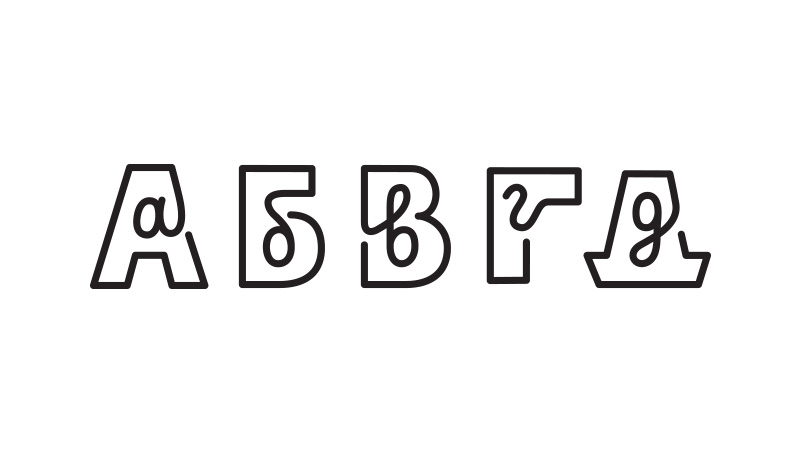
Шрифт из одной линии для обработки «по вектору» — Вопросы по шрифтам
Не в первый раз возникает необходимость написать что-нибудь эдакое одной линией.. Так, сейчас немаленький заказик на изготовление металлических штампиков для оттиска по пластилину.. Кто как выходит из положения? (я как-то давнееенько баловался- свой шрифт делал.. Убей- не помню- в какой программе, как и зачем
На сколько я понимаю, но нельзя создать линейный шрифт ни TTF-ный ни посткриптовый — т.
к. они по своей природе должны быть залитыми контурами…. Может я не прав — тогда опровергните — буду только рад…
Для номерков я нарисовал (вернее племяшку попросил — ей надо было чертежи готовить) файл с контурными буквами чертежных шрифтов (все по ГОСТу!!!!) ….
А так ежели очень надо, то можно воспользоваться ArtCAM-овскими линейными шрифтами (работают чесно), но в них нет наших кириллических букв (а так полноправная их работа и по кривым и прочее…), или делать файлы для таких вещей из инженерного софта — там линейные шрифты есть…
Для номерков я нарисовал (вернее племяшку попросил — ей надо было чертежи готовить) файл с контурными буквами чертежных шрифтов (все по ГОСТу!!!!) ….
Только что экспериментировал с АвтоКадом и АртКамом, экспортировал в EPS.
Шрифт из одной линии, правда угловатый, но все же результат
Будем шукать ишо.. Есть вообще в природе такая фигня- называется «скелетизация шрифтов».. Любой шрифт, (хоть иероглифический) можно представить в виде центральной линии в кривых Безье.. Где-то я колупался с этим хозяйством.. Нарою- расскажу.. Если нарою
Позвонил племяшке — она не против… Просили в студию — получайте (два типа шрифта отрисованные в Copel)…
Красиво, хотя пользоваться ими трудозатратно. Но для простеньких работ — вполне сойдет. Нужно искать этот, как там его, «скелетизатор»…
Племяшке и ее дяде спасибо! Вот- нарыл тут кое-что.. Живые шрифты ГОСТ. Можа кому пригодится.. Мне уже пригодились..
Пробовал поработать с линейными шрифтами в Корел-12 (там есть возможность сохранять в TTF- формате и т.д.). Замысел такой- перевести линейный шрифт BIG’а в объекты и сохранить в файле шрифта.. Пока сопротивляется.. Сохраняется, блин в файле шрифта токо одна буква
Спасибо за шрифты — класс — но в одну линию как-то не верится, что получится…. Ладно: попробую найти у нас в городе мастера по шрифтам ( у него в свое время шрифты для написания ответов сканвордов и сотовых сканвордов заказывал — а с два десятка его правильных шрифтов на разных компашках находил — правильно делает) — проконсультируюсь, и если возможно — закажу у него шрифтик с учетом минимизации подъема инструмента ( что-бы полностью нарисован был одной линией)….
В одну и не получится.
. Я пробую взять Ваш линейный, перевести его в объект (т.е. «толщина» будет 0,1 мм ), грохнуть среднюю линию и уже «ЭТО» сохранить в файле шрифта..
Тогда особого выигрыша не будет — ведь идея монолинейного шрифта — время отработки его почти в 2 раза меньше, чем этого же начертания сделанного V-гравировкой -т.к. она делается по средней линии, но двойным проходом… Я, например, задумывал использовать монолинейные цифирки для номерков по акрилу при большущих тиражах и демпинговых ценах на номерки (правда клиенты при таких ценах шарахались, т.к. предлагал на 30% дешевле самых дешевых цен города, а тираж просто за разумные сроки иначе было сделать нельзя, т.